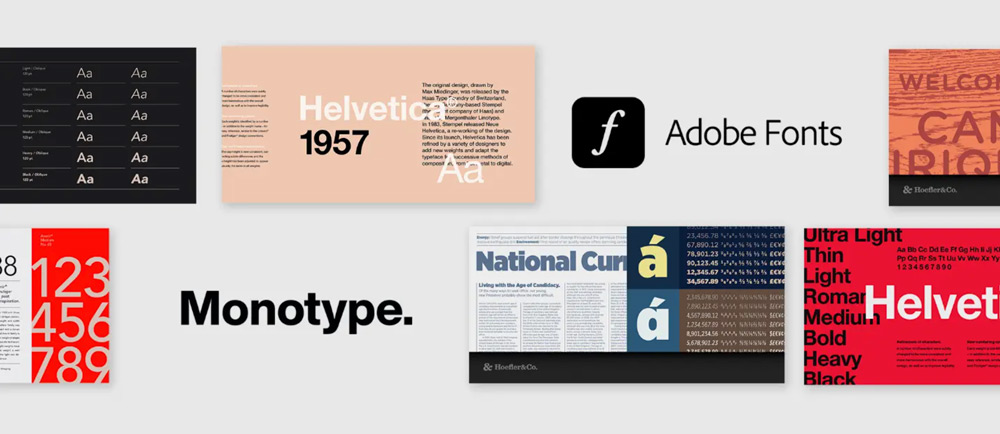
Adobe erweitert Adobe Fonts um 1500 Schriften
Adobe hat das Angebot an Schriftarten für Nutzer der Creative Cloud deutlich vergrößert. Ab sofort stehen 1500 zusätzliche Fonts zur Verfügung. Zu den Neuzugängen zählen bekannte Schriften wie die Helvetica, Times New Roman, Arial, Avenir, Gotham und Proxima Nova. Außerdem wurde die globale Bibliothek um Schriften für Arabisch, Chinesisch, Japanisch, Koreanisch, Thailändisch, Hindi u. v. m. erweitert. Über die Adobe Fonts Bibliothek, die in vielen Abonnements der Creative Cloud enthalten ist, haben Kreative wie Fotografen, Grafikdesigner und Illustratoren Zugriff auf über 30000 verschiedene Schriftarten, die sie frei in ihren Projekten verwenden können.
Die hinzugefügten Fonts stammen aus verschiedenen Stilrichtungen. Von klassischen Serifenschriften über moderne serifenlose Fonts bis hin zu dekorativen und handschriftlichen Varianten ist alles dabei. Die neuen Schriftarten stammen von bekannten Schriftanbietern wie Monotype und unabhängigen Designern.
Adobe Fonts, früher bekannt als Typekit, ist ein Dienst, der Schriftarten für digitale und gedruckte Anwendungen bereitstellt. Die Schriften können sowohl online in Webseiten als auch offline in Printprojekten verwendet werden. Alle Fonts sind lizenziert und dürfen kommerziell eingesetzt werden.